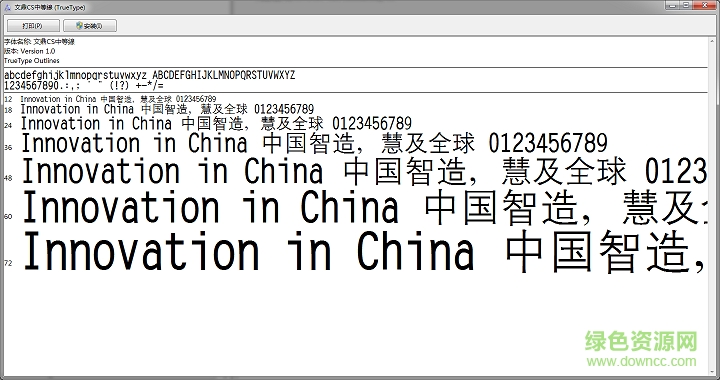
denshancsegmediumgb字體(文鼎cs中等線)是一款等線字體,字體骨骼分明,樸素端正,看起來簡潔爽朗,閱讀性不錯!書籍、報章、雜志的正文等都可使用這款字體!
它們的特點是都有幾乎相等的線條,前者好像漢字中的黑體,完全拋棄了字腳,只剩下字母的骨骼,顯得樸素端正,十分清晰,但過于平板,因此也叫做無字腳體。